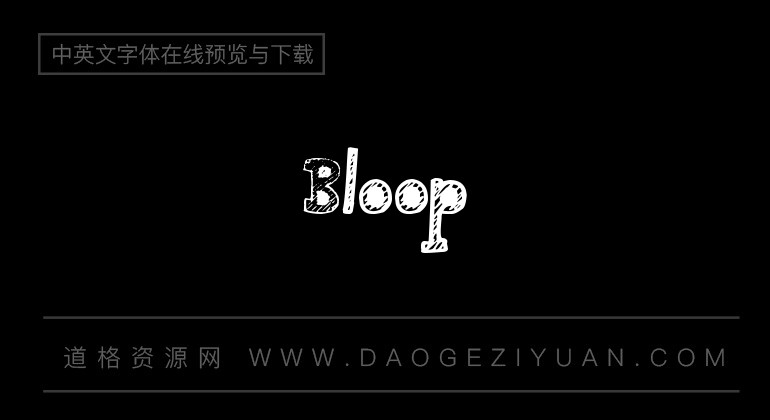
Bloop
? Bloop字体是一款由英国设计师Rory MacLeod创作的一款漂亮的手写字体,它具有温柔可爱的特色,同时也具有流行的特质。它的字母笔画细腻,有着温暖的气息,可以轻松地创造出温暖的气氛。它的笔画柔和,可以带来温柔的感觉,这种字体适合用于节日卡片、海报和其他类型的设计。
Bloop是一款非常不错的手写艺术字体,具有很好的视觉感,适合于文化类的宣传设计、商业类品牌的广告和产品包装设计以及个性化文字排版等较多场景。